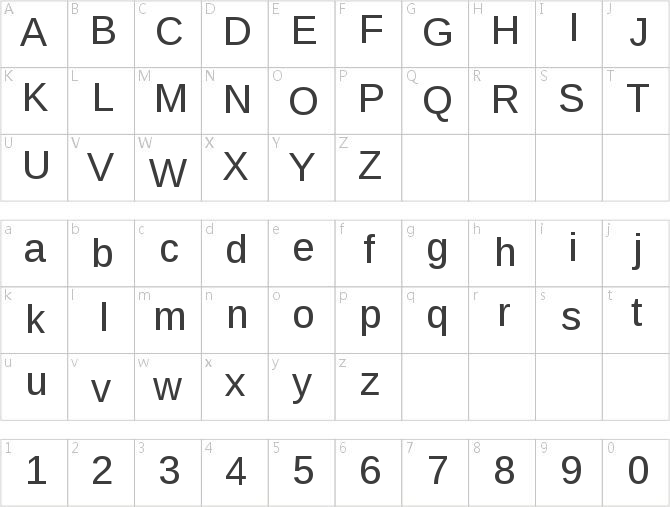
LiberationSans-Regular
LiberationSans-Regular介紹
LiberationSans-Regular字體字庫是一款讓人賞心悅目、百看不厭的英文字體,適合各類廣告和產品包裝設計應用,字體大小0.11MB,格式為ttf字體,上傳用戶是woslxn,作者/版權方為未知